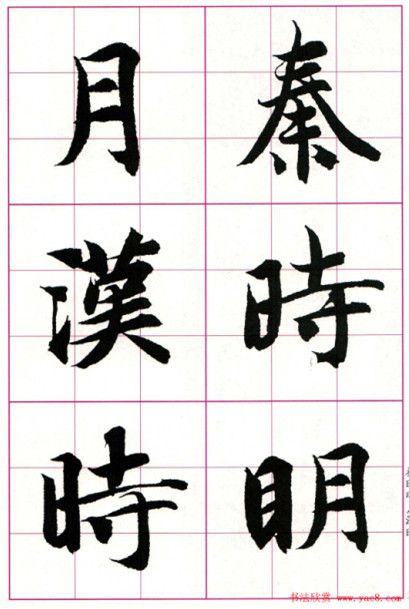
本练字字帖模板包含的四首古诗分别是王昌龄的《出塞》、王维的《渭城曲》、李白的《峨眉山月歌》、李白的《客中行》,每首古诗提供钢笔楷书字体的原文和译文,另有智永毛笔楷书字体的原文,每首6页,共24页,可通过百度网盘下载。
《出塞》
作者:王昌龄
秦时明月汉时关,万里长征人未还。
但使龙城飞将在,不教胡马渡阴山。
《渭城曲》
作者:王维
渭城朝雨浥轻尘,客舍青青柳色新。
劝君更饮一杯酒,西出阳关无故人。
《峨眉山月歌》
作者:李白
峨眉山月半轮秋,影入平羌江水流。
夜发清溪向三峡,思君不见下渝州。
《客中行》
作者:李白
兰陵美酒郁金香,玉碗盛来琥珀光。
但使主人能醉客,不知何处是他乡。
智永,字智永,王右军(王羲之)七世孙,智永善书,书有家法。智永还将王羲之作为传家之宝的《兰亭序》,带到云门寺保存,云门寺有书阁,智永禅师居阁上临书20年。他所写的《千字文》清何绍基说:“笔笔从空中来,从空中住,虽屋漏痕,犹不足以喻之”。
张怀瓘将古今善书法者分成三品:神品、妙品、能品。智永的行书入能品,隶书、章草、草书皆入妙品。可见智永书法成就已达到相当高的水平。都穆《寓意编》云:“智永真草千文真迹,气韵飞动,优入神品,为天下法书第一”;